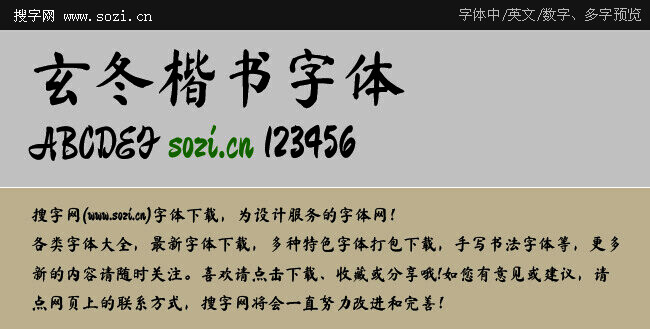
玄冬楷書字體
搜字網(wǎng)提供一款玄冬楷書字體中文書法字體下載,玄冬楷書(Xuandong Kaishu)字體是一款基于谷歌開源字體《馬善政毛筆楷書》的拓展字體。在原版的基礎(chǔ)之上修復(fù)了錯(cuò)誤的字形并添加豎排排版的特性。玄冬楷書字體是一款手寫風(fēng)格的毛筆書法字體,字型大方典雅,書寫自然,充滿文化氣息。適合圖書設(shè)計(jì)、包裝設(shè)計(jì)、海報(bào)設(shè)計(jì)等應(yīng)用。